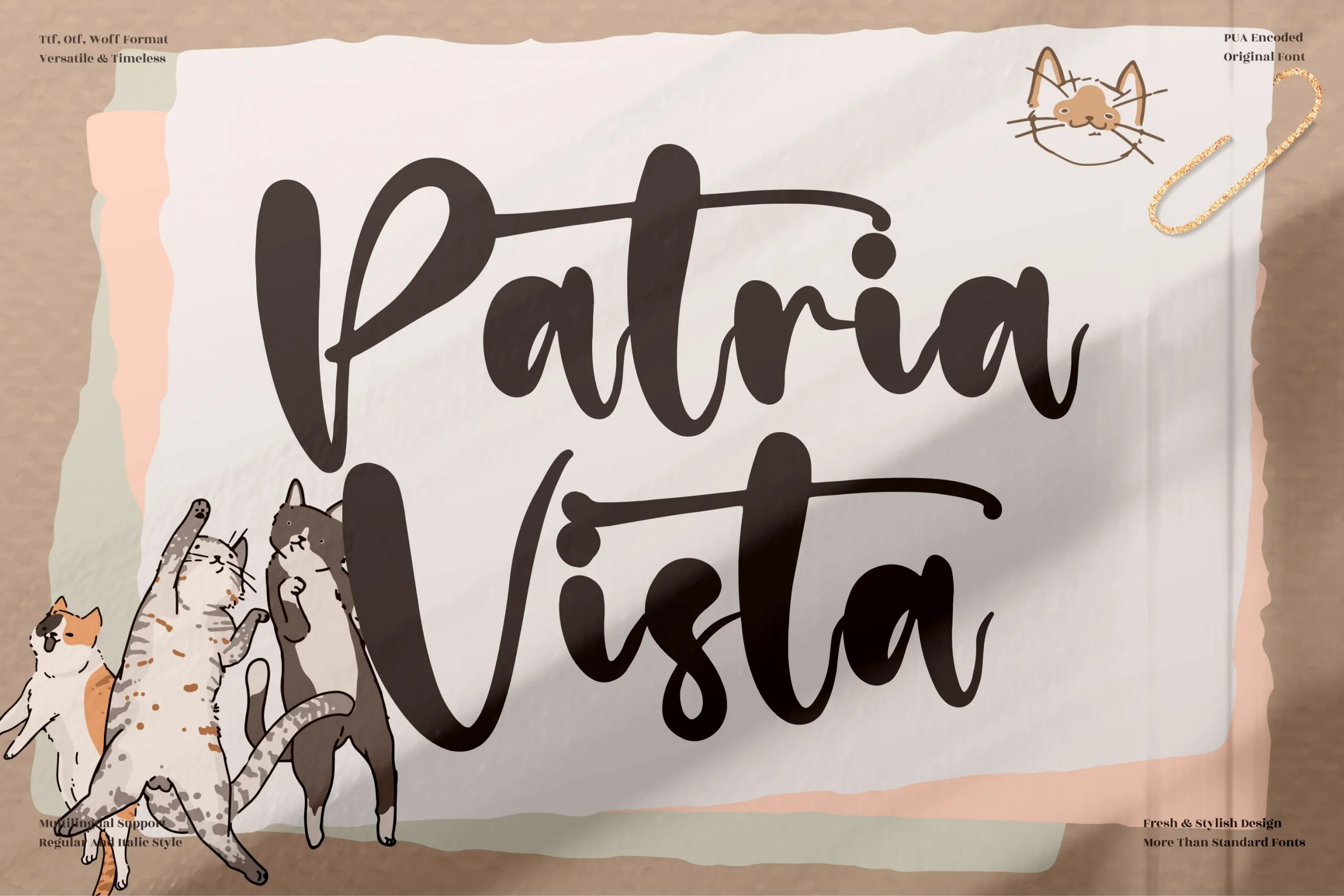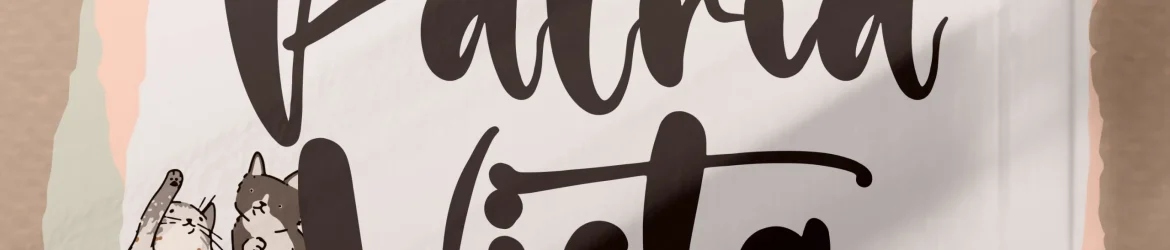
A fonte ‘Patria Vista’ é uma encantadora tipografia romântica perfeita para projetos diversos que buscam um toque delicado e elegante. Seja para criar logotipos, trabalhos de marca, designs de móveis, embalagens de produtos, tigelas, citações, postais, sacolas de compras, camisetas, capas de livros, cartões de nome, cartões de convite, etiquetas, fotos ou qualquer outro projeto que necessite de uma pitada de esplendor e beleza tipográfica. Seja para eventos especiais ou simplesmente aqueles momentos do dia a dia, ‘Patria Vista’ trará um toque único e inspirador a cada criação. Uma fonte perfeita para aqueles projetos que precisam de uma pitada de romance na tipografia.